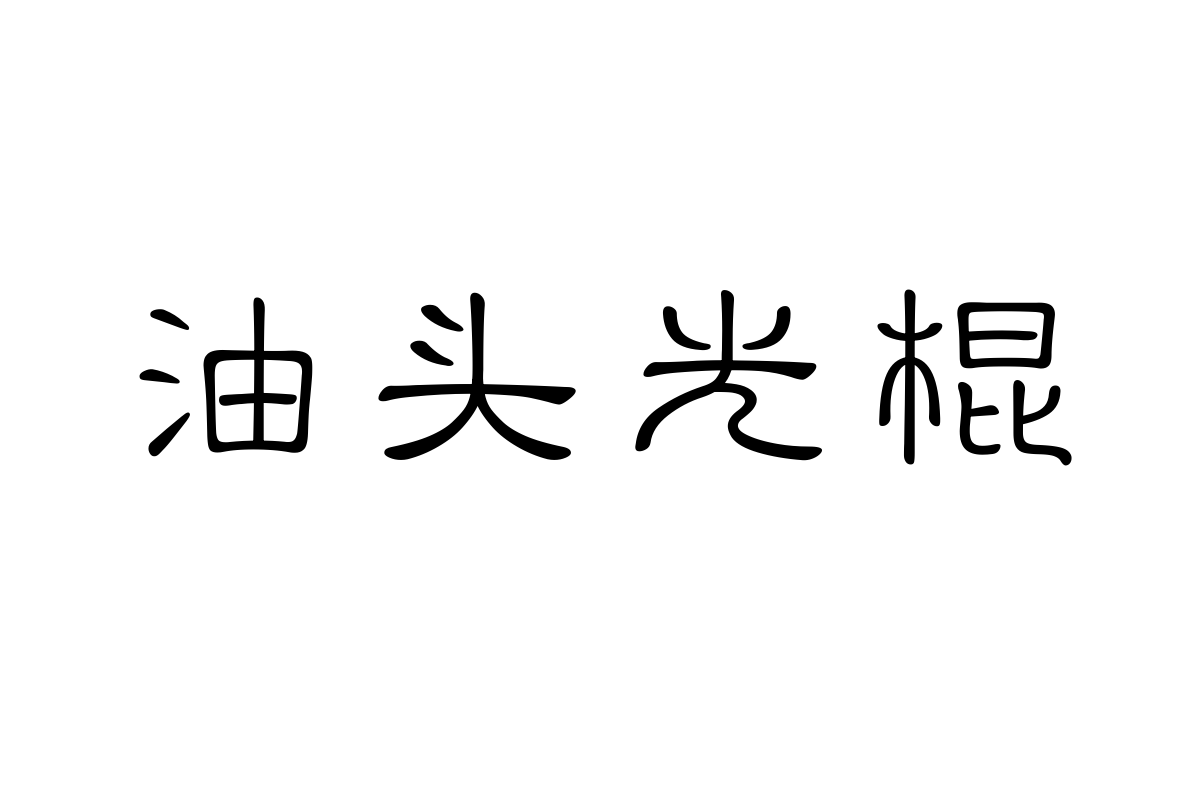
文道现代篆书字体是一款具有现代感的篆书字体,它结合了传统篆书的精髓与现代设计元素,创造出一种既古典又时尚的视觉效果。该字体适用于需要展示传统文化韵味的场合,如文化展览、艺术设计、书籍封面等。
文道现代篆书字体的特点如下:
1. 字形结构:该字体保留了篆书的基本笔画和结构,但在细节上进行了简化和优化,使其更加符合现代人的审美习惯。
2. 风格特点:文道现代篆书字体在保持篆书传统韵味的同时,融入了一些现代设计元素,如简洁的线条、流畅的曲线等,使得整体风格更加时尚。
3. 应用场景:该字体适用于需要展示传统文化韵味的场合,如文化展览、艺术设计、书籍封面等。同时,也适合用于商业广告、品牌宣传等领域,以提升品牌形象。
总之,文道现代篆书字体是一款兼具传统韵味与现代设计的优质字体,适用于各种需要展示传统文化的场合。